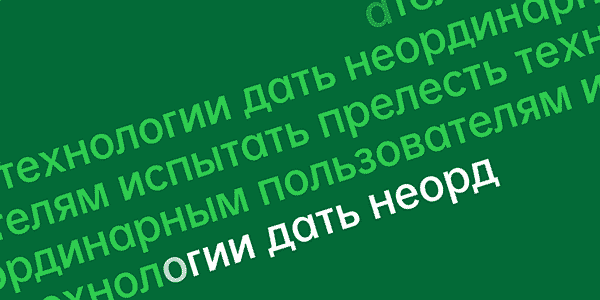
适合logo的字体有哪些?15种英文字体推荐
在品牌越来越重要的时代,我们几乎每时每刻都在和各种各样的品牌logo⁠(在新标签页或窗口中打开)打交道。字体是品牌视觉系统中的重要组成部分,不管品牌logo如何设计,所使用的字体都要能够体现品牌形象。这篇文章为你推荐4类不同风格的适合用在logo设计中的15款英文字体,希望对你的工作有所帮助。
01 古典衬线风格
衬线字体历史悠久,最早可以追溯到古罗马时期的碑刻。衬线就是在每个字母笔画的最末端,添加一个稍微往上翘的曲线,或者将线条加粗,看起来就像多了一个小三角形。
与其他粗细一致的字体相比,衬线字体更能在细节处表现笔画的变化,给人的感觉是庄重、华贵和权威,因此多用于历史、时尚、学术和文化领域。
目前比较常用的又适合logo的衬线字体是时尚杂志常用的Didot和Bodoni、谷歌旧版logo所使用的Catull、服饰品牌GAP所用的Spire Regular、IBM标志所用的ITC Lubalin Graph厚衬线字体和常见的 Times New Roman字体。
02 几何无衬线风格
无衬线字体的字母粗细没有明显变化,风格偏向简练、现代和中性,适用于电器、汽车、航空和通讯等行业。圆润柔和的无衬线字体可以营造一种友好、亲近的感觉,许多科技公司喜欢使用简洁的无衬线字体,显得非常人性化。
最常见的无衬线风格logo的字体就是Helvetica,是松下电器、无印良品和英特尔的标志字体。如今许多品牌开始采用无衬线风格的标志,其字体也是在Helvetica的基础上重新设计的。
其他适合logo的有苹果爱用的Myriad字体、《时代》杂志封面的标志性字体Optima、BBC标志字体Gill Sans以及同样属于瑞士风格的Univers字体和复古风格的ITC Bauhaus字体。
Futura是20世纪最成功的字体之一,锐利而不张扬,简洁清晰,呈现出一种乐观的现代主义风格。来自包豪斯年代的Futura字体至今仍是许多品牌的爱用字体,如路易威登、宜家和乐高玩具等。
03 手写华丽风格字体
西方人使用鹅毛笔所书写的文字就是一种典型的手写英文字体——哥特体,带有宗教、个性和反叛的意味,一些潮牌爱用这种字体,如Vetements。
19世纪初,美国书法家史宾赛设计一款线条极具流动感的草书字体,后来被称为Spencerian Script,也就是可口可乐的字体,看起来飘逸随行又华丽。许多品牌还喜欢使用创始人签名的手写字体,更具个性特色和品牌传承感,如Harrods百货公司、Paul Smith高端时装和迪士尼等。
04 品牌专属的定制字体
上世纪,大型企业会通过支付版权费从字体公司那里获得专属使用的企业字体。现如今,字体被更多的品牌看作是表现企业文化和价值观的一种方式,于是越来越多的企业开始采用定制字体,当然也有缩减预算和增加语言兼容性的原因。
最开始是微软、苹果这样的大型科技公司推出定制字体,后来小型的品牌也跟进了这个潮流,例如爱彼迎、Netflix、OPPO和腾讯等。